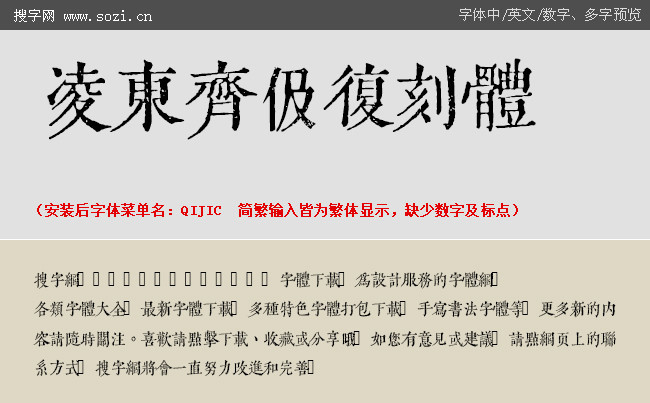
凌東齊伋復(fù)刻體
搜字網(wǎng)給大家提供一款凌東齊伋復(fù)刻體中文字體下載, 凌東齊伋復(fù)刻體采用半自動(dòng)計(jì)算機(jī)視覺和OCR對(duì)《李長(zhǎng)吉歌詩》和《淮南鴻烈解》進(jìn)行掃描,通過程序處理后再手動(dòng)選擇適合的字型,最后導(dǎo)出成字體文件,凌東齊伋復(fù)刻體是對(duì)古籍進(jìn)行處理而得到的字體,所以只有繁體字形。在使用字體的過程中,如果輸入簡(jiǎn)體字會(huì)直接映射成繁體字形。而且可以免費(fèi)商用!適合海報(bào)設(shè)計(jì)、包裝設(shè)計(jì)等宣傳廣告等應(yīng)用。